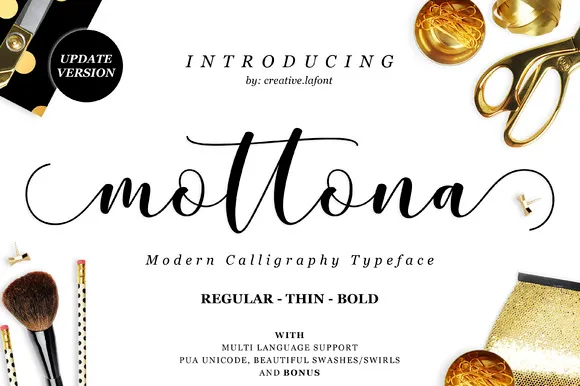
Mottona Script Font – Download Grátis
Olá, designers! Se você está procurando uma fonte moderna para seus projetos digitais, você vai adorar a Mottona Script Font. Esta é uma fonte de escrituração que oferece letras cuidadosamente moldadas para tornar seu texto ainda mais bonito e atraente. Seu design moderno traz um toque único e contemporâneo para qualquer projeto que escolha, seja ele cartões de casamento, convites, cartazes, carteirinhas de nome, mensagens, cabeçalhos de blog, marcas de identidade visual, logotipos, moda, roupas, e até mesmo a correspondência. Com essa fonte em sua coleção, você está sempre pronto para criar elementos de design incríveis para qualquer finalidade. Mottona Script é perfeita não apenas por seu estilo moderno, mas também pela versatilidade inigualável que oferece para diferentes projetos. Seja um trabalho gráfico de moda, uma marca personalizada ou até mesmo o texto em sua próxima newsletter do blog – a Mottona Script tem a capacidade de adaptar-se perfeitamente ao seu projeto. Adquira agora a sua e descubra como essa fonte pode revolucionar a maneira como você cria textos digitais. Seja criativo, seja lúdico, seja original – o design digital está à sua disposição.
Designer: Creative.lafont